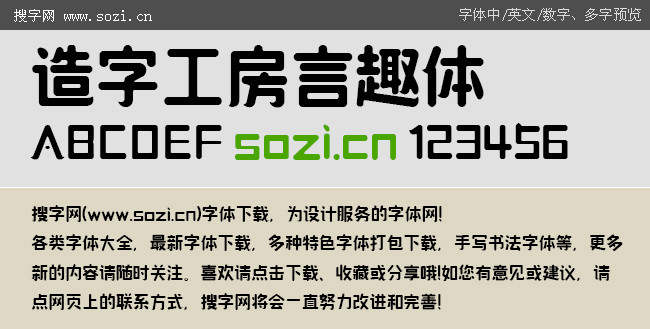
造字工房言趣體
搜字網(wǎng)給大家提供一款造字工房言趣體中文字體下載,造字工房言趣體筆畫圓勻娟秀,筆觸淳厚拙樸,巧用大量圓角,使之更具親和力的同時(shí)與整體特點(diǎn)相得益彰,于柔雅中見靈動俏皮,給人溫潤可愛之感。適合應(yīng)用于海報(bào)設(shè)計(jì)、報(bào)頭設(shè)計(jì)、網(wǎng)頁標(biāo)題等應(yīng)用。(本字體為個(gè)人非商用版,如需要商用請聯(lián)系官方購買版權(quán))